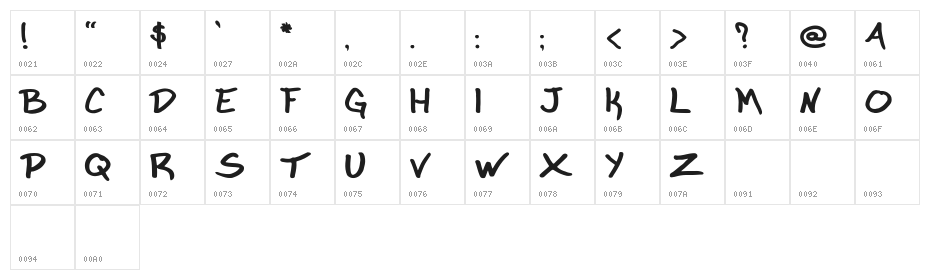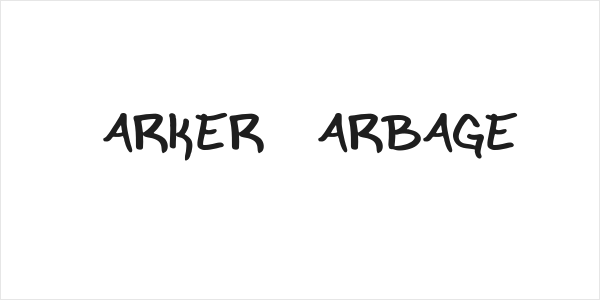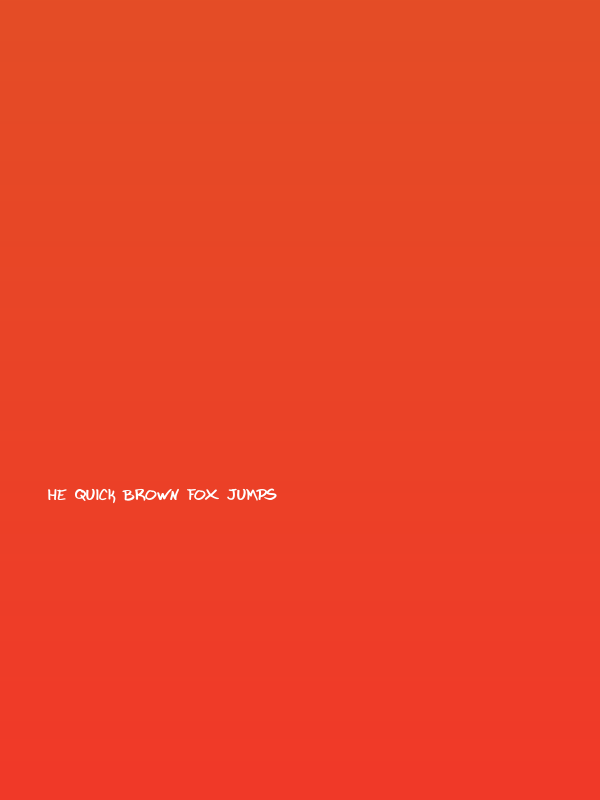
Marker Garbage Font
| Estilo general | Casual, Playful |
| Caso de uso | Headlines, Logos, Informal Text |
| Proyectos propuestos | Ideal for greeting cards, children's books, playful branding, and casual invitations. |